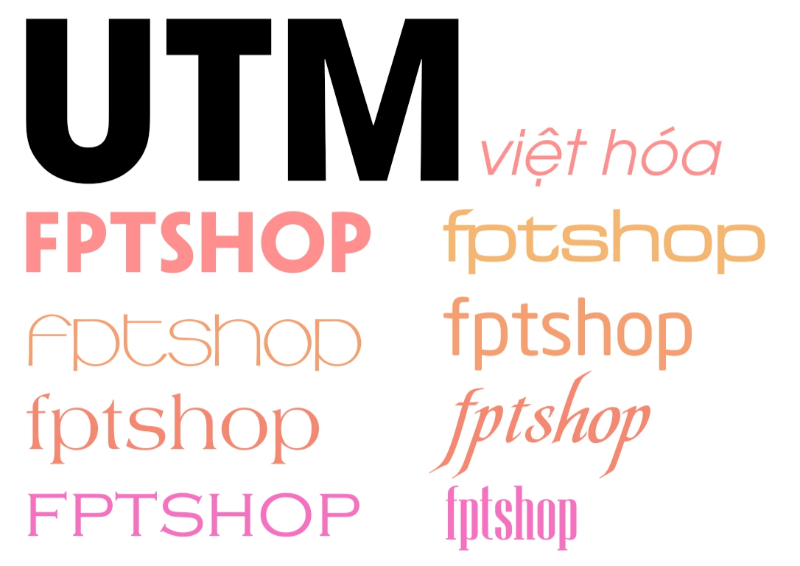
Đối với bất kỳ ai làm việc trong lĩnh vực thiết kế, từ dân designer chuyên nghiệp, marketer, sinh viên cho đến dân văn phòng, chắc hẳn bạn đã từng gặp qua vấn đề khó chịu này: Tìm được một font chữ Tây cực kỳ ưng ý, nhưng khi gõ tiếng Việt thì các chữ cái có dấu lại bị biến thành ô vuông, hoặc dấu ngã, dấu hỏi bay lơ lửng lệch lạc khỏi con chữ. Đó là lúc chúng ta cần đến Font chữ Việt hóa.
Font chữ Việt hóa không chỉ giúp hiển thị tiếng Việt đầy đủ, đúng dấu mà còn giữ được tính thẩm mỹ và tinh thần của bản thiết kế. Một bộ font phù hợp có thể làm thông điệp trở nên rõ ràng, chuyên nghiệp và cảm xúc hơn. Trong bài viết này, mình sẽ chia sẻ đến các bạn cẩm nang toàn tập giúp bạn hiểu, phân loại, lựa chọn và sử dụng font chữ Việt hóa một cách chuyên nghiệp và an toàn nhất.
Font chữ Việt hóa là gì?
Về bản chất, phần lớn các font chữ đẹp trên thế giới được thiết kế dựa trên bảng mã Latinh tiêu chuẩn, thường bỏ qua các ký tự đặc biệt của tiếng Việt (vốn có hệ thống dấu phụ khá phức tạp như sắc, huyền, hỏi, ngã, nặng và các mũ ă, â, ê, ô, ơ, ư).
Font chữ Việt hóa là những font gốc của nước ngoài đã được các designer hoặc các nhóm chuyên làm font tại Việt Nam can thiệp, vẽ thêm các ký tự có dấu này sao cho đồng bộ với phong cách, độ dày và tỷ lệ của nét chữ gốc. Nhờ đó, chúng ta có thể gõ tiếng Việt một cách hoàn hảo mà không lo vỡ lỗi.
Phân loại Font chữ Việt hóa phổ biến nhất hiện nay
Thay vì tải hàng trăm font về máy khiến hệ thống nặng, khó quản lý và dễ rối khi thiết kế, bạn nên hiểu rõ đặc điểm của từng nhóm font chữ Việt hóa. Khi nắm được phong cách, ưu điểm và mục đích sử dụng của từng loại font, bạn sẽ chọn đúng font cho từng dự án, giúp thiết kế đẹp hơn, chuyên nghiệp hơn và truyền tải thông điệp hiệu quả hơn.
Sans-Serif – Font không chân hiện đại, tối giản
Sans-Serif là nhóm font không có nét gạch nhỏ ở đầu hoặc cuối chữ. Kiểu chữ này thường có đường nét gọn gàng, rõ ràng và dễ đọc, đặc biệt phù hợp với môi trường hiển thị kỹ thuật số như website, ứng dụng, điện thoại và máy tính.
Nhờ phong cách tối giản, hiện đại, font Sans-Serif thường tạo cảm giác chuyên nghiệp, trẻ trung và dễ tiếp cận. Đây là lựa chọn an toàn cho những thiết kế cần sự rõ ràng, tinh gọn và dễ đọc.
Font gợi ý: Roboto, Montserrat, Work Sans, UTM Avo, SVN-Gilroy.
Ứng dụng: Thiết kế UI/UX, website, landing page, slide thuyết trình doanh nghiệp, banner quảng cáo công nghệ, startup, thương hiệu hiện đại.
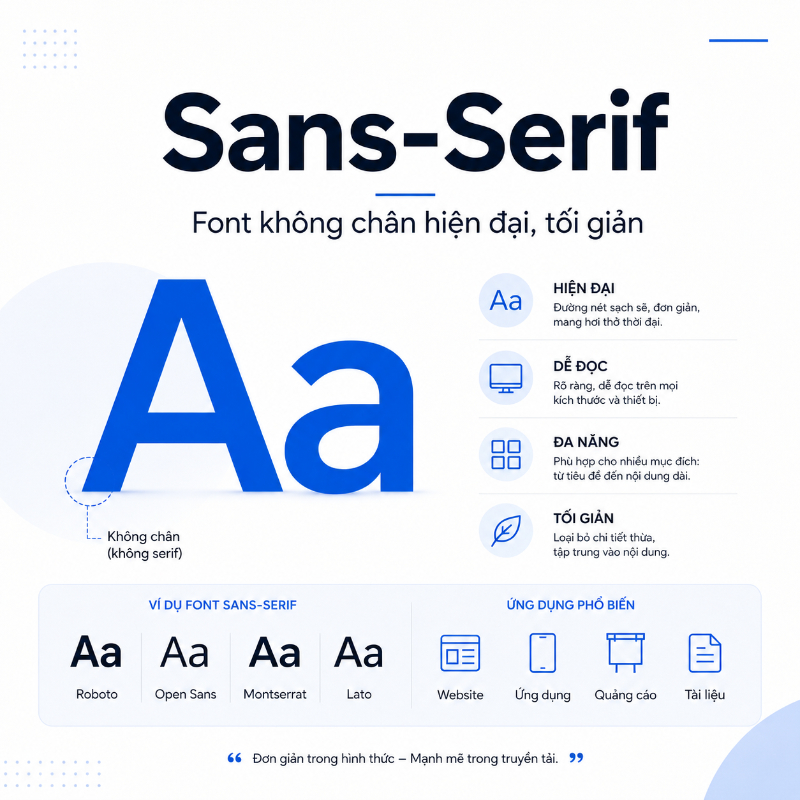
Serif – Font có chân cổ điển, sang trọng
Serif là nhóm font có các nét gạch nhỏ ở phần đầu hoặc cuối nét chữ. Chính chi tiết này giúp chữ có cảm giác mềm mại, trang trọng và giàu tính truyền thống hơn so với font không chân.
Font Serif thường gợi lên sự thanh lịch, đáng tin cậy, học thuật và cao cấp. Vì vậy, nhóm font này rất phù hợp với các thiết kế cần thể hiện sự tinh tế, chiều sâu thương hiệu hoặc cảm giác sang trọng.
Font gợi ý: Playfair Display, Vollkorn, Lora, DFVN Aveline, MTD-Bodoni.
Ứng dụng: Logo thương hiệu thời trang cao cấp, bìa sách, tạp chí, catalogue, thiệp cưới sang trọng, ấn phẩm in ấn và các nội dung cần cảm giác chỉn chu, uy tín.
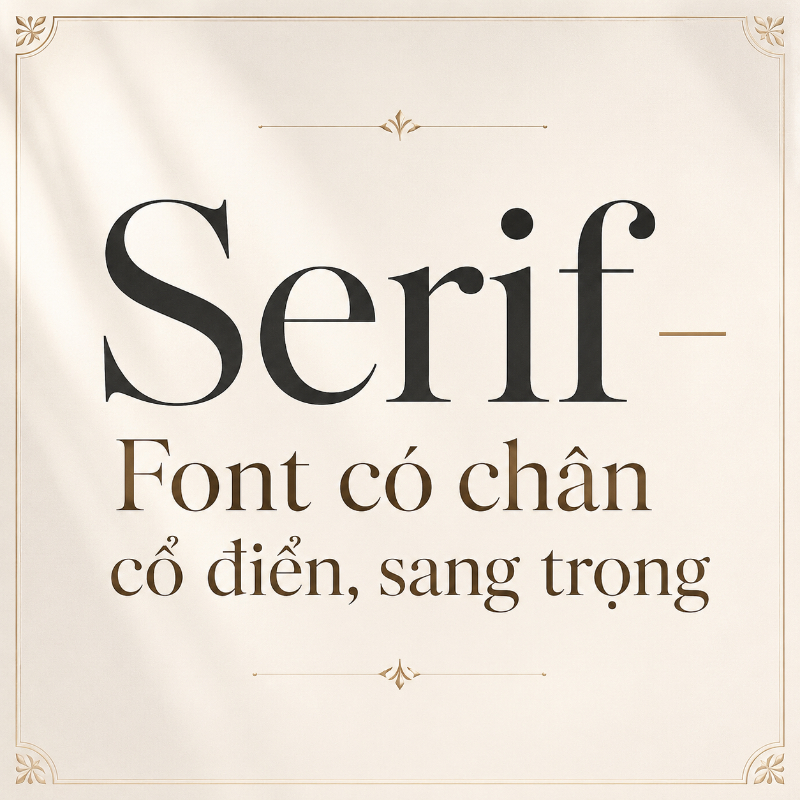
Script/Handwritten – Font viết tay bay bổng, giàu cảm xúc
Script hoặc Handwritten là nhóm font mô phỏng nét chữ viết tay, thư pháp, chữ ký hoặc nét cọ tự nhiên. Đặc điểm nổi bật của nhóm font này là sự mềm mại, uyển chuyển và mang đậm dấu ấn cá nhân.
Font viết tay thường tạo cảm giác gần gũi, nghệ thuật, lãng mạn hoặc thủ công. Tuy nhiên, nhóm font này nên dùng có chọn lọc, chủ yếu cho tiêu đề, điểm nhấn hoặc câu trích dẫn, không nên dùng cho đoạn văn dài vì dễ gây khó đọc.
Font gợi ý: Dancing Script, Pacifico, TH Milyah, Photograph Signature, iCiel Autography.
Ứng dụng: Thiết kế quote, thiệp cưới, logo chữ ký, bao bì sản phẩm handmade, mỹ phẩm organic, thương hiệu cá nhân, bài đăng mạng xã hội mang cảm xúc nhẹ nhàng.
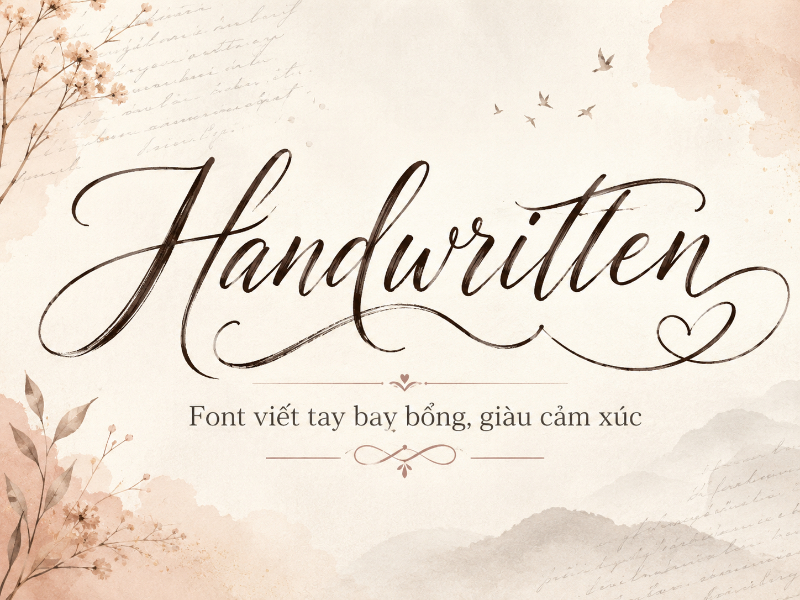
Display/Decorative – Font trang trí phá cách, độc đáo
Display hoặc Decorative là nhóm font được tạo ra để gây ấn tượng mạnh ngay từ cái nhìn đầu tiên. Nét chữ thường có kích thước lớn, dày, nhiều hiệu ứng hoặc mang phong cách riêng như retro, cổ điển, game, sci-fi, brush, horror hoặc vintage.
Nhóm font này không ưu tiên khả năng đọc dài mà tập trung vào khả năng thu hút thị giác. Vì vậy, bạn nên dùng font Display cho tiêu đề lớn, poster, banner hoặc các điểm nhấn quan trọng trong thiết kế.
Font gợi ý: SVN-Rubra Costa, FzKT2, FzVNG, Potta One và các font retro, game, brush Việt hóa.
Ứng dụng: Poster phim, banner sự kiện, thumbnail YouTube, tiêu đề quảng cáo, thiết kế game, ấn phẩm giải trí, chiến dịch truyền thông cần sự nổi bật và khác biệt.
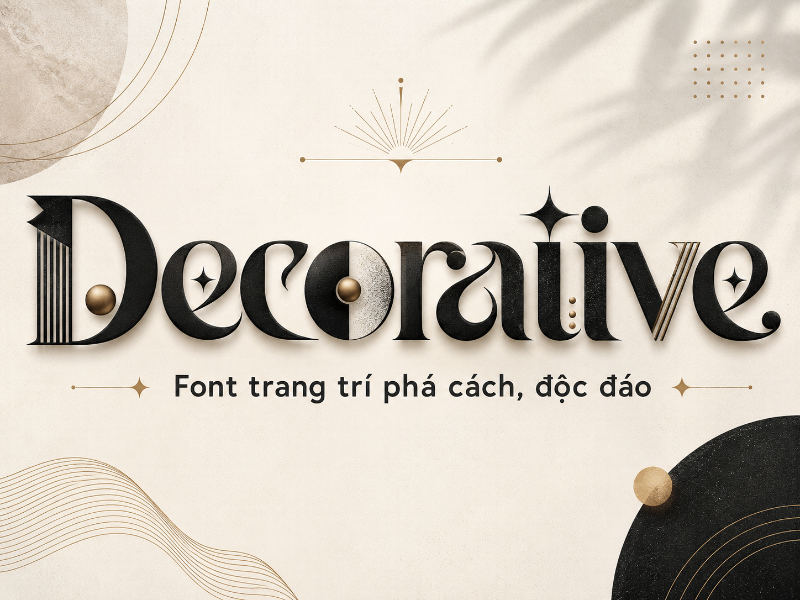
Bí quyết chọn và kết hợp Font chữ chuyên nghiệp
Có nhiều font chữ đẹp chưa chắc đã tạo nên một thiết kế đẹp. Điều quan trọng là bạn phải biết chọn đúng font, phối hợp hợp lý và đảm bảo nội dung dễ đọc. Dưới đây là những nguyên tắc cơ bản nhưng rất quan trọng khi sử dụng font trong thiết kế.